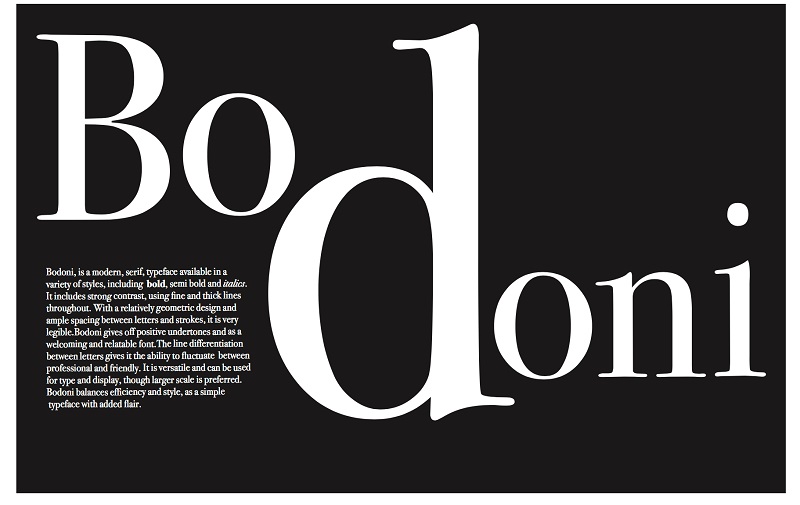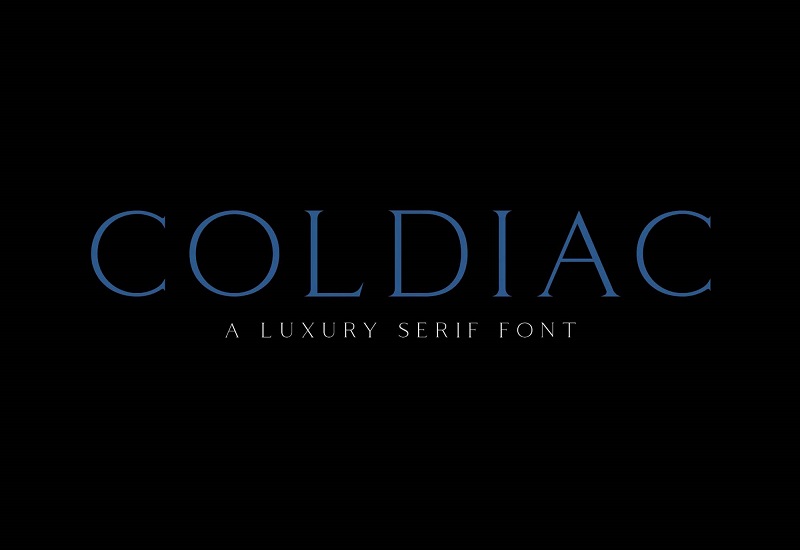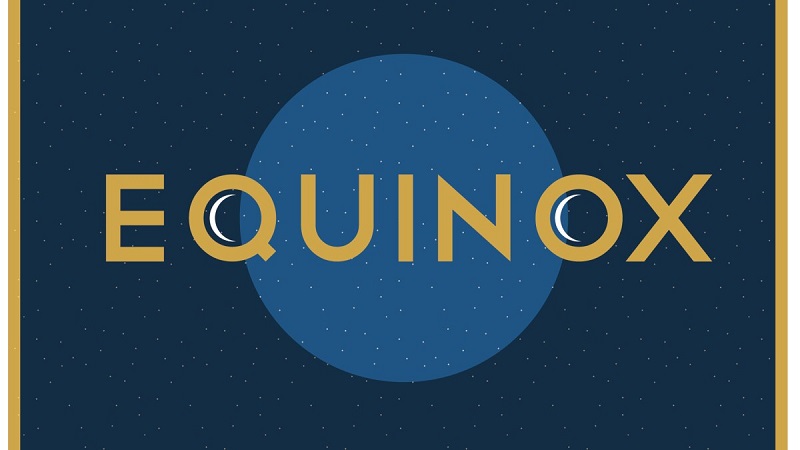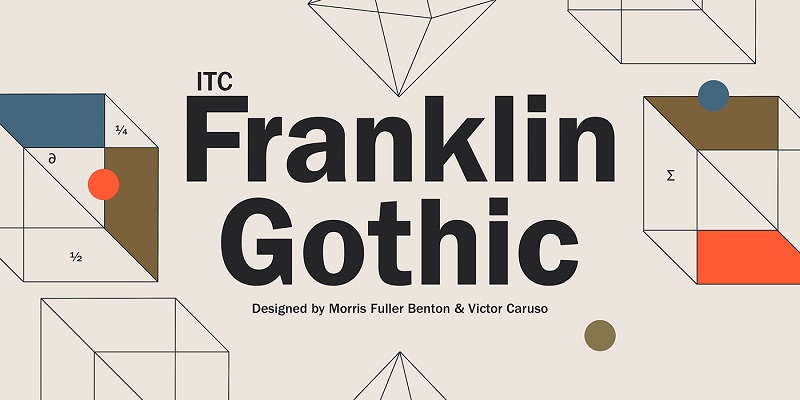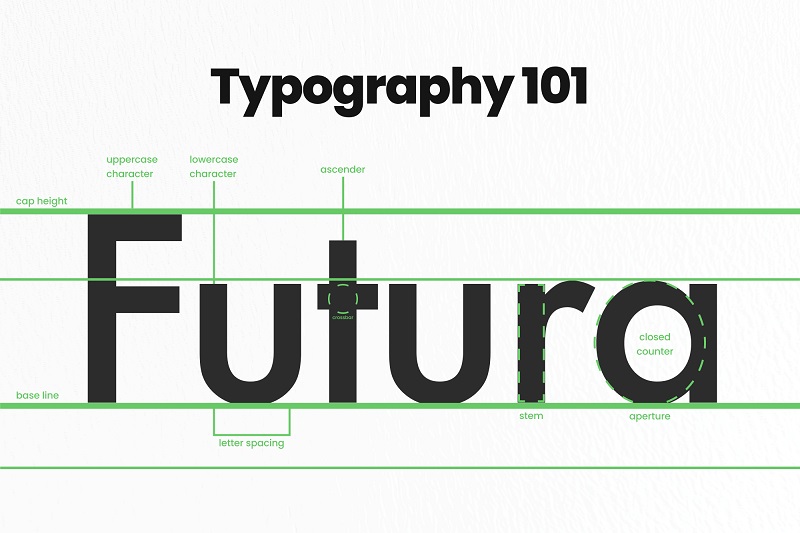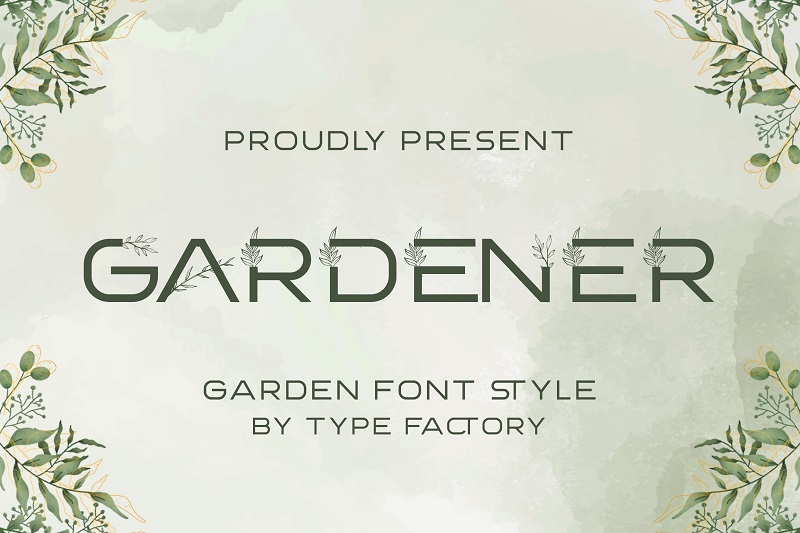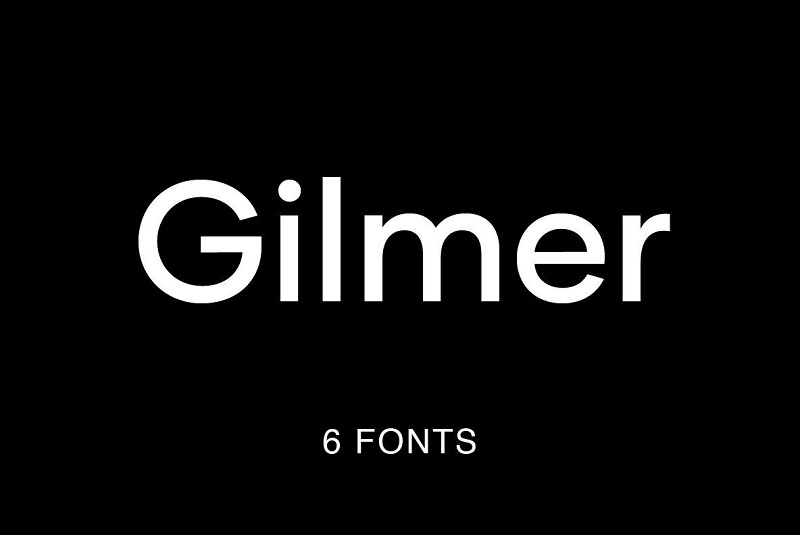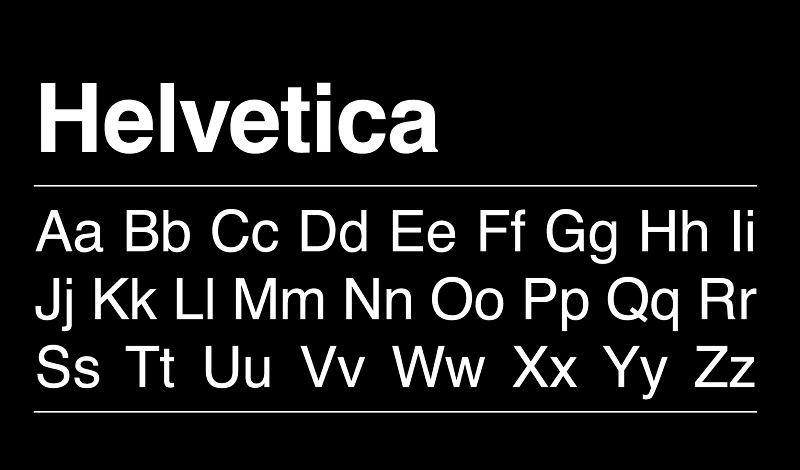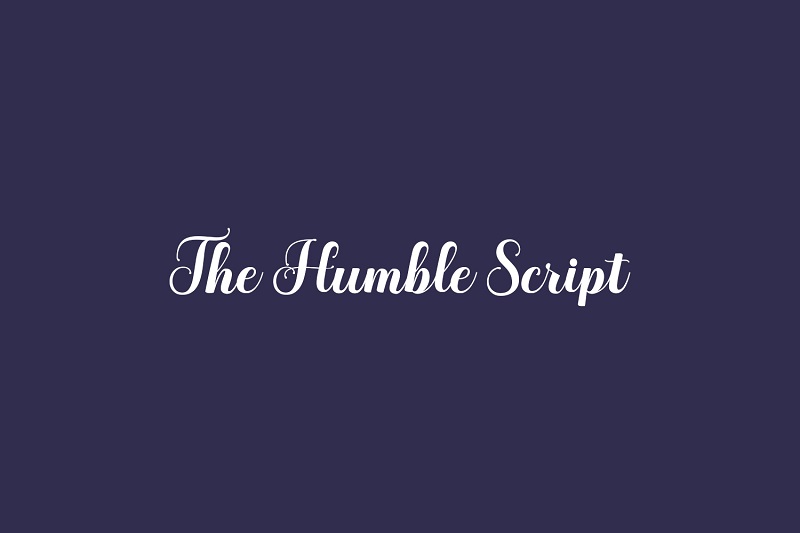
Top 12 Font Chữ Thiết Kế Poster Đẹp Dành Cho Các Designer Chuyên Nghiệp
Trong thiết kế đồ họa, việc lựa chọn font chữ thiết kế poster đóng vai trò quan trọng, giúp truyền tải thông điệp một cách ấn tượng và thu hút người xem ngay từ cái nhìn đầu tiên. Một font chữ phù hợp không chỉ nâng cao thẩm mỹ mà còn tạo nên sự chuyên nghiệp cho sản phẩm thiết kế. Bài viết dưới đây của Vietkey sẽ giới thiệu đến bạn top 12 font chữ poster đẹp, phổ biến và phù hợp với các designer chuyên nghiệp.
Font chữ thiết kế poster là gì?
Font chữ thiết kế poster là những kiểu chữ được chọn lọc và thiết kế đặc biệt nhằm phục vụ cho việc trình bày nội dung trên poster một cách nổi bật, dễ đọc và thu hút sự chú ý của người xem. Khác với các font chữ dùng trong văn bản thông thường, font chữ thiết kế poster thường có đường nét rõ ràng, kiểu dáng sáng tạo và tính thẩm mỹ cao, giúp truyền tải thông điệp một cách trực quan và ấn tượng. Việc lựa chọn font chữ phù hợp sẽ giúp poster trở nên sống động, dễ nhớ và tạo được điểm nhấn riêng cho thương hiệu hoặc sự kiện mà bạn muốn quảng bá.
Ngoài yếu tố thẩm mỹ, font chữ thiết kế poster còn ảnh hưởng trực tiếp đến khả năng truyền đạt thông tin. Một font chữ cân đối, dễ đọc sẽ giúp người xem nhanh chóng nắm bắt nội dung, đồng thời nâng cao trải nghiệm thị giác và cảm giác chuyên nghiệp cho sản phẩm. Chính vì vậy, việc hiểu rõ đặc điểm và chức năng của các loại font chữ dành cho poster là bước quan trọng để các designer có thể tạo ra những thiết kế vừa đẹp mắt vừa hiệu quả.
Font chữ thiết kế poster
Top 12 font chữ thiết kế poster ấn tượng và phổ biến nhất
Việc lựa chọn font chữ thiết kế poster phù hợp là yếu tố then chốt để tạo nên những thiết kế nổi bật và thu hút người xem. Dưới đây là top 12 font chữ ấn tượng và phổ biến nhất mà các designer chuyên nghiệp thường sử dụng cho các poster của mình.
Franklin Gothic
Franklin Gothic là một trong những font chữ nổi tiếng được thiết kế bởi Morris Fuller Benton vào đầu thế kỷ 20. Với kiểu dáng mạnh mẽ, rõ ràng và dễ đọc, Franklin Gothic nhanh chóng trở thành lựa chọn ưa thích cho các tiêu đề báo chí thời bấy giờ. Không chỉ giới hạn trong in ấn, font chữ này còn được sử dụng rộng rãi trên các áp phích quảng cáo phim, bảng hiệu thương mại và các ấn phẩm quảng cáo khác. Nhờ sự kết hợp giữa tính hiện đại và khả năng thu hút người xem, Franklin Gothic vẫn giữ vị trí quan trọng trong thiết kế poster đến tận ngày nay.
Franklin Gothic
Futura
Futura là một font chữ thiết kế poster mang phong cách hình học, được lấy cảm hứng từ trường phái Bauhaus. Với các chữ cái thanh mảnh, cân đối và dễ đọc, Futura kết hợp hài hòa giữa nét cổ điển và hiện đại, giúp thông tin hiển thị rõ ràng ngay cả ở cỡ chữ nhỏ. Nhờ những ưu điểm này, font chữ thường được ứng dụng trong thiết kế logo, tài liệu quảng cáo và các bản copy, mang lại cảm giác chuyên nghiệp và tinh tế. Futura vẫn là lựa chọn ưa thích của nhiều designer khi tạo các poster nổi bật và sang trọng.
Futura
Helvetica
Helvetica là một trong những font chữ thiết kế poster phổ biến nhất trong thiết kế đồ họa hiện đại nhờ tính miễn phí và khả năng đọc cao. Font chữ này mang đến vẻ gọn gàng, tinh tế, phù hợp với nhiều phong cách thiết kế khác nhau, từ poster quảng cáo đến ấn phẩm thương mại. Tuy nhiên, do các chữ cái trong Helvetica được đặt khá sát nhau, khi sử dụng ở cỡ chữ nhỏ, thông tin có thể trở nên khó đọc và gây cảm giác rối mắt. Dù vậy, Helvetica vẫn luôn là lựa chọn ưa thích của nhiều designer chuyên nghiệp nhờ sự linh hoạt và hiện đại.
Helvetica
Gilmer
Gilmer là một font chữ thiết kế poster mang phong cách cổ điển, nổi bật với khả năng tạo ra các bản in sắc nét và chất lượng cao. Sự linh hoạt trong thiết kế giúp Gilmer dễ dàng áp dụng cho nhiều loại ấn phẩm, từ poster quảng cáo đến logo thương hiệu. Nhờ nét thanh lịch, cân đối và khả năng hiển thị rõ ràng, font chữ này nhanh chóng trở thành lựa chọn ưa thích của các designer khi muốn tạo ra những thiết kế vừa chuyên nghiệp vừa thu hút. Gilmer tiếp tục được đánh giá cao trong các dự án thiết kế hiện đại và cổ điển.
Gilmer
Equinox
Equinox là một font chữ cho poster mang phong cách khoa học viễn tưởng, lý tưởng để tạo nên các thiết kế hiện đại và độc đáo. Với các chữ cái tối giản, mảnh mai, Equinox giúp nội dung hiển thị rõ ràng và dễ đọc, mang lại cảm giác tinh tế và tương lai. Tuy nhiên, font này không bao gồm các chữ cái viết thường, điều này đôi khi có thể gây khó khăn trong việc trình bày những đoạn văn dài hoặc chi tiết. Dù vậy, Equinox vẫn là lựa chọn lý tưởng cho các poster muốn nổi bật với phong cách sáng tạo và độc đáo.
Equinox
Bodoni
Bodoni là một font chữ thiết kế poster mang vẻ sang trọng và đẳng cấp, ra đời vào cuối thế kỷ 18 với phong cách cổ điển tinh tế. Nét đặc trưng của Bodoni là sự kết hợp hài hòa giữa các đường nét dày và mỏng, tạo nên cảm giác thanh lịch nhưng vẫn nổi bật. Font chữ này thường được ứng dụng trong các ấn phẩm văn học cổ điển, poster nghệ thuật hay thiết kế cao cấp, giúp truyền tải sự tinh tế và chuyên nghiệp. Nhờ tính thẩm mỹ vượt thời gian, Bodoni vẫn là lựa chọn lý tưởng cho các designer muốn tạo dấu ấn riêng.